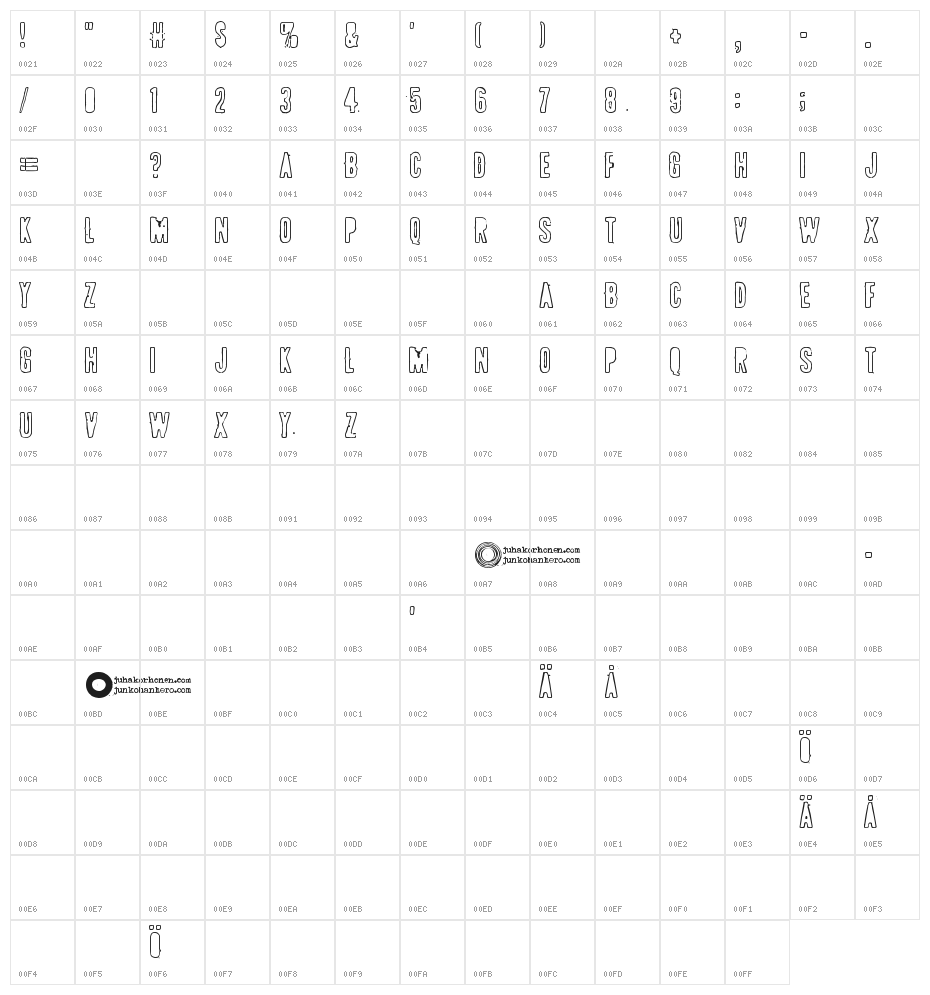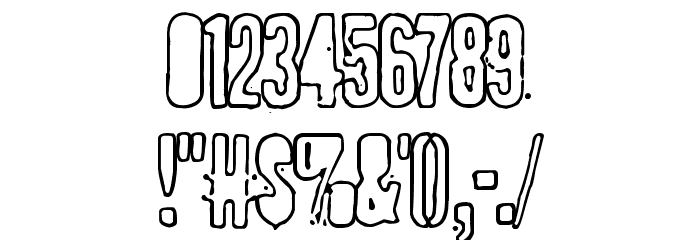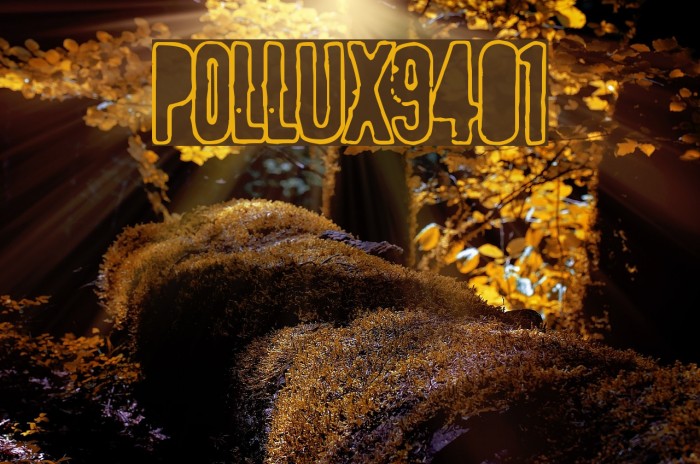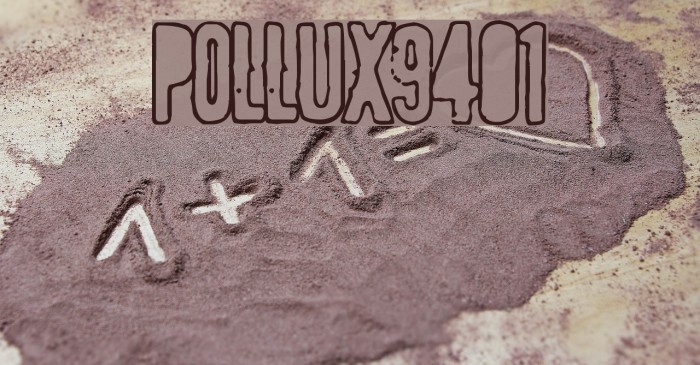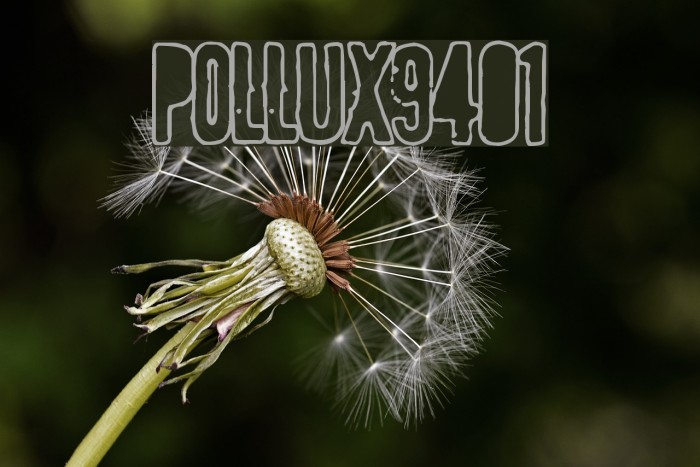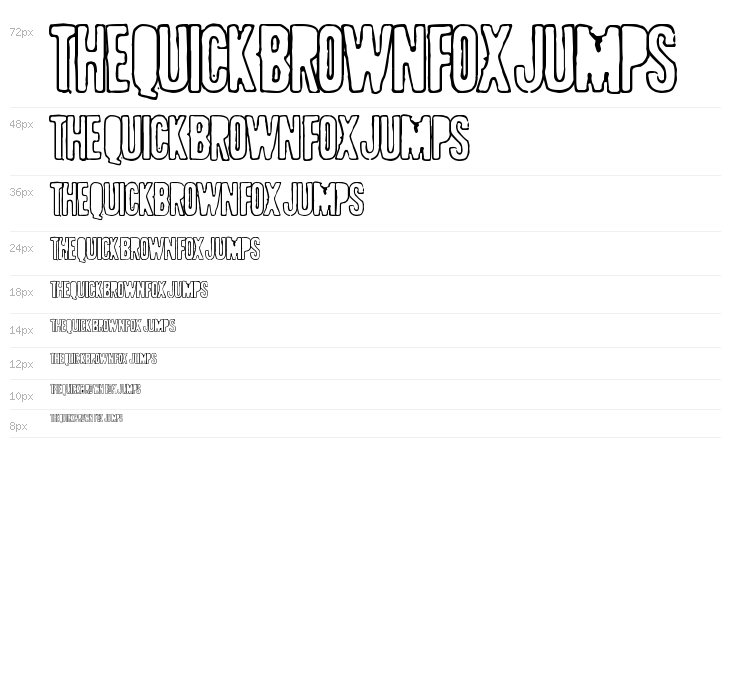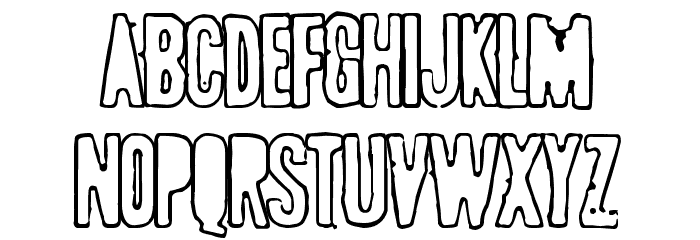
POLLUX9401 Font
✎ Distorted Eroded
POLLUX9401 MAJUSCULES
POLLUX9401 MINUSCULES
POLLUX9401 AUTRES CHARS
| Catégories | Distorted Eroded |
| Projets proposés | Ideal for posters, album covers, branding for vintage-themed products, or any design needing a rugged, eye-catching typeface. |